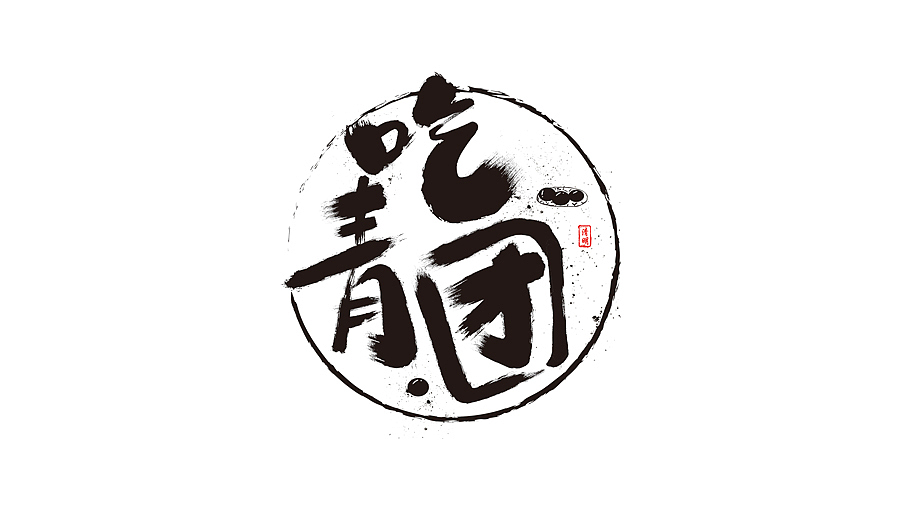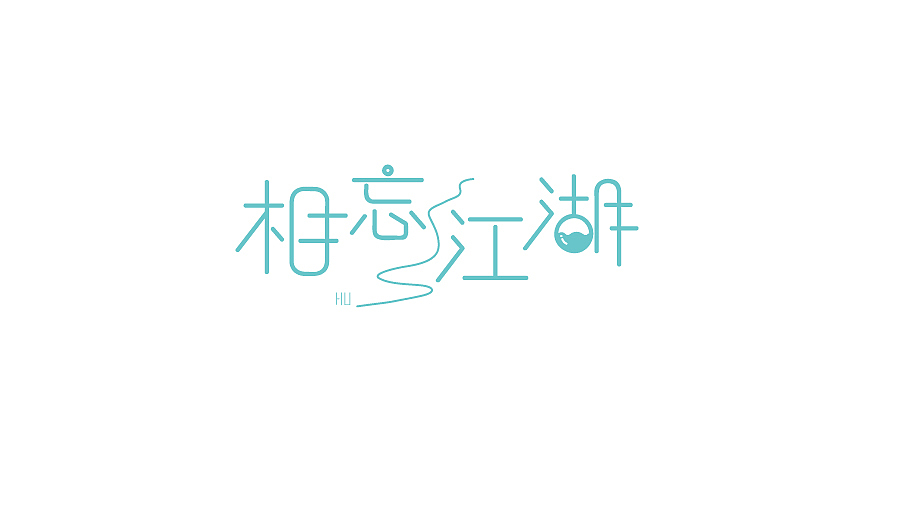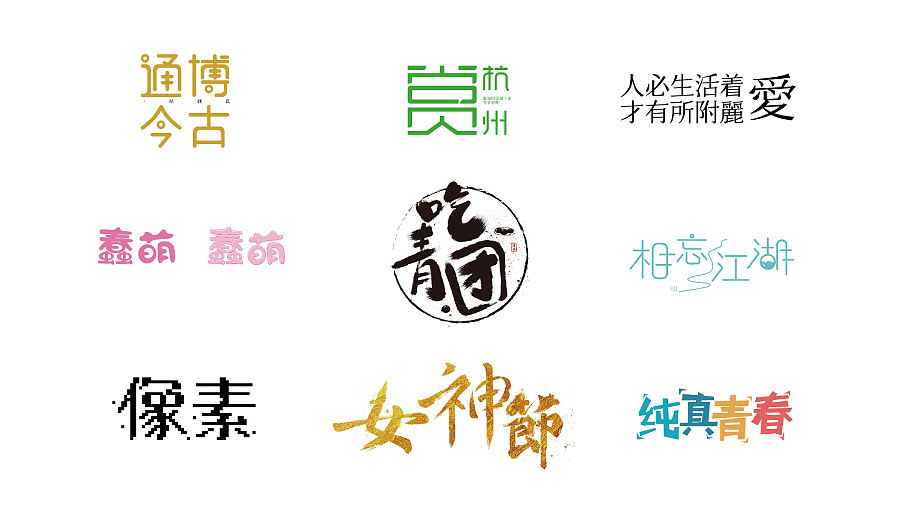
字体练习-|不同风格字体|
字体设计真是一件非常有趣的事。
这些是我平时的字体练习,主要是针对不同风格字体的习作,发上来和大家分享一下。
比较圆润和儒雅的一组字,通过笔画的空间构成和某些笔画的细节变化做出想要的效果。
“团”字的创作着实费了很大的劲,难度在于“团”与前两个字体风格上的统一。
比较简单的一组字,我喜欢叫这种“好看、好用又易做”的字体叫糖水字。嗯~还是蛮甜的。
“人必生活着爱才有所附丽”,难道不是吗?
浪漫美好的爱情是要有所依托的,是要有一定的物质条件的。
离我的要求有点远,但也是一种尝试。PS~开心老头的套索字真的做的很好看。
这是微信公众号的名字的原型,后来的完善稿把“杭州”中间的两行诗句去掉了。“赏”的中间有个对话框,意喻通过图文推送的形式欣赏、观赏、赏玩杭州。中间的诗句是欧阳修的《采桑子》中的一句“谁知闲凭阑干处,芳草斜晖”。
嗯,是的,相忘于江湖。
像素字
男神节,毛笔字体。
同样是毛笔字体。